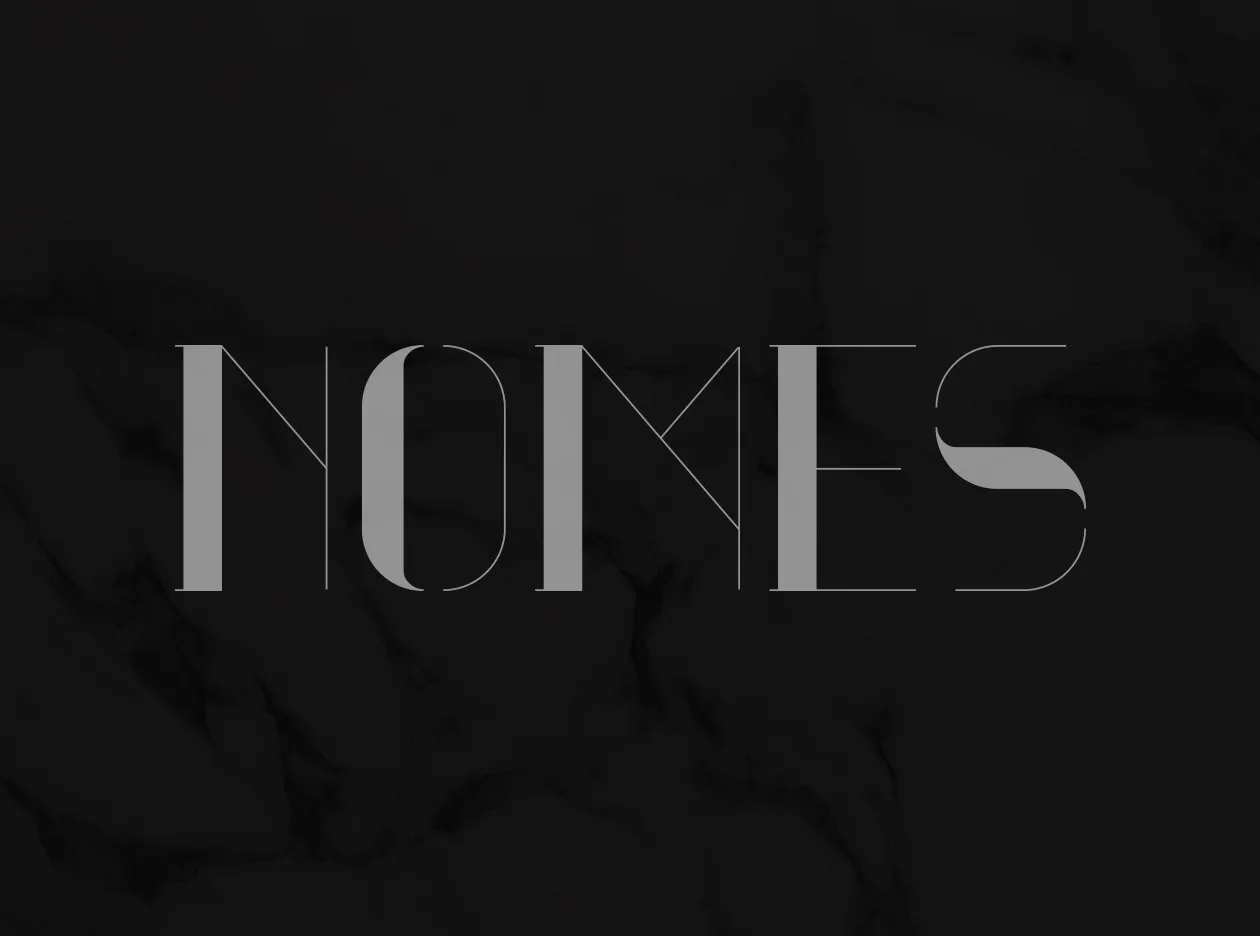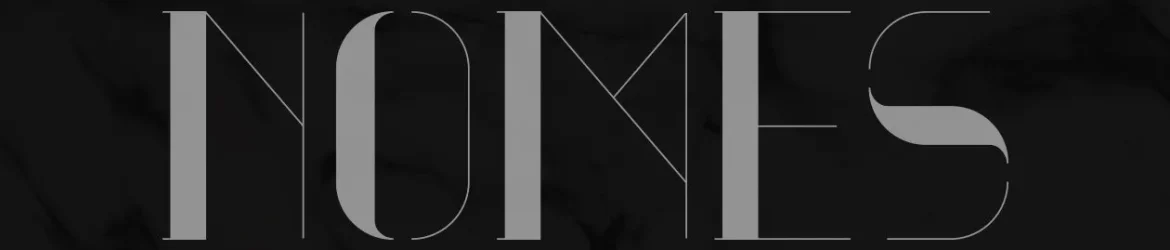
Nomes é uma tipografia romana elegante que oferecemos gratuitamente tanto para uso pessoal quanto comercial por designers. A característica mais notável dessa fonte está no traço fino que rodeia metade de cada letra, contribuindo para a simplicidade e beleza do design. O encanto da Nomes reside na contraste entre os elementos finos e grossos em cada alfabético, criando um aspecto arquitetônico único e versátil. Ideal tanto para gráficos profissionais quanto para projetos pessoais, a Nomes é uma opção excelente para designers que buscam uma estética sofisticada e moderna. Para quem está procurando por um roteador de letra elegante com elementos contrastantes, a Hamilton certamente se destaca como uma excelente escolha.